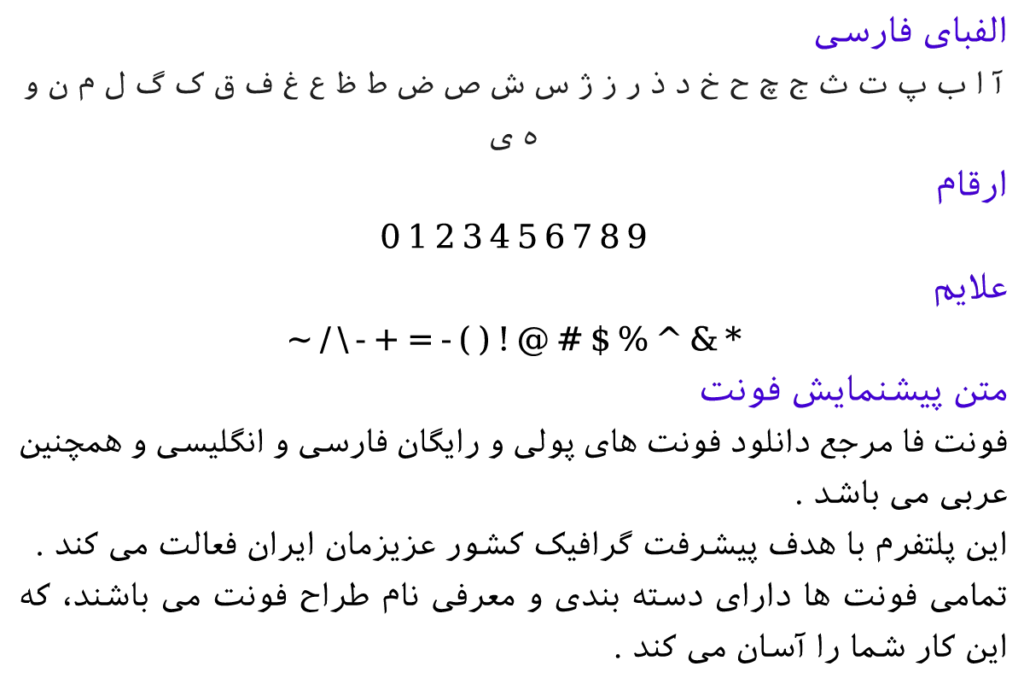
فونت فارسی ایرانیان سریف – Iranian Serif
طراح فونت: هومن مهر نوع فونت: فونت متن
توضیحات و معرفی فونت ایرانیان سریف
فونت فارسی ایرانیان سریف ( Iranian Serif ) از مجموعه فونت های آزاد می باشد، همچنین نوع فونت متن می باشد.
فونت فوق العاده زیبای معرفی شده توسط هومن مهر طراحی و ساخته شده است.
ایرانیان سریف فونتی خوشگل است که تفاوتی زیادی با فونت ایرانیان سانس دارد.
همچنین فونت ایرانیان سریف در یک وزن معمولی است.
شعر زیبای وطنم نوشته شده با این تایپ فیس